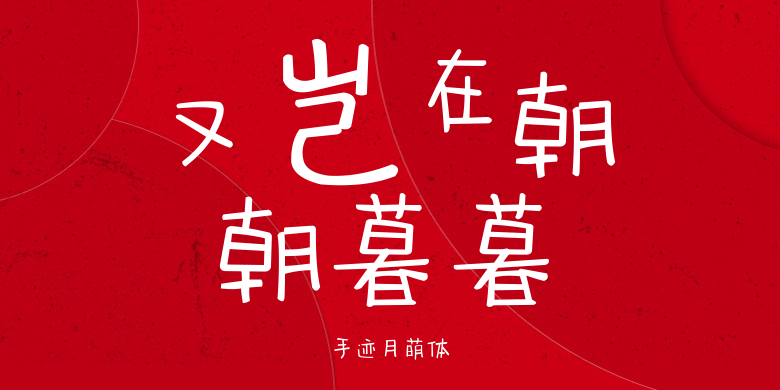
手迹月萌体
手迹月萌体,这款字体结构工整、笔画清晰,兼顾美观与易读性,适用于标题、正文、海报、包装、LOGO 等多种场景。字形优雅稳定,风格百搭耐看,适配日常排版与创意设计,让文字呈现更舒适、更具质感。手迹月萌体一笔一画,皆是细节,以均衡的比例、流畅的线条打造舒适视觉体验,字形端正大气,风格简约现代。无论是商业设计、品牌宣传还是日常排版,都能轻松驾驭,让文字更有格调与力量。手迹月萌体字体下载。